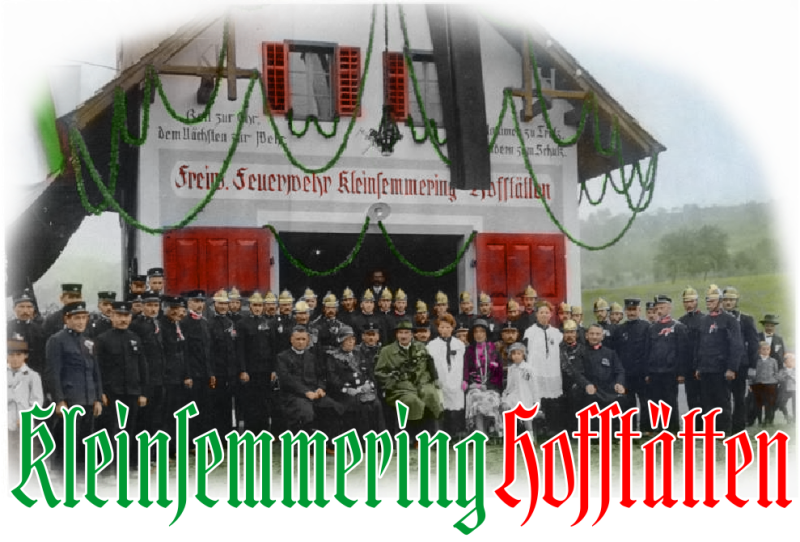
ich suche diese Schriftart (Alp Grüm)
Und zwar suche ich (zwecks Modellbau) die folgende Schriftart (siehe Bild im Anhang !)
… darf gerne auch eine Empfehlung sein, wer mir diese Schrift erstellen kann am Computer
Sinn und Zweck
Diese einzelnen Buchstaben sollen dann für den Nachbau eines Gebäudes im Modell dienen (um allenfalls Decals anzufertigen oder … um die einzelnen Buchstaben lasern zu lassen)
Hallo @Bergkette, da die einzelnen Ausführungen gleicher Buchstaben sich zum Teil erheblich unterscheiden und gestalterisch in schwankender Qualität bei unterschiedlichsten Genres bedienen, dürfte es sich hier um komplett handgemachte Lettern ohne eine Satzschrift als Vorlage handeln.
Wenn die exakte Wiedergabe dieser Formen wichtig sein sollte, kann dich u. a. vielleicht @catfonts bei der 1:1-Digitalisierung unterstützen.
Wenn es stattdessen auch ein handwerklich ordentlicheres Schriftbild auf Basis einer existierenden Satzschrift sein darf, kann ich mir beispielsweise eine Zenith DJR vorstellen*, die ihrerseits auf einem Schriftzug an einem Gebäude basiert.
Ich dachte auch schon lange, dass es sich hierbei um einzelne Buchstaben ohne wirkliches Schriftbild handelt. Da das Modell möglichst nahe am Vorbild sein soll, möchte ich natürlich auch gerne die Buchstaben entsprechend so nachbilden.
Du schreibst weiter … dass man evt. die Buchstaben digitalisieren lassen könnte ?
Ja, der macht sowas, Ein Beispiel hierzu:
Das ist z.B.solch eine, aus einer Hausanschrift erstellten Schriftart. Vorlage hierzu ist das dargestellte Foto (es war Schwarzweiß)
Aufgabenstellung war es, die original-Beschriftung am Originalgebäude wieder herzustellen, um Zuge eines Erweiterungsbaus.
Jetzt sieht das Haus in Kärnten (bis auf die Sinnsprüche die in den Besprechungsraum im Inneren umgezogen sieht es wieder wie damals aus.
die Hauptbeschriftung, und die Sprüche teilweise abweichende Buchstabenform haben, sind da 2 Schriften entstanden.